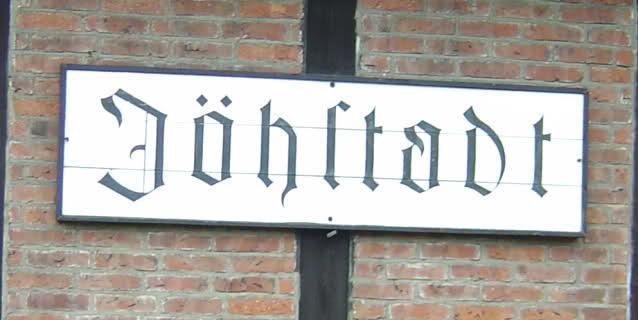
Frakturschrift gesucht
Welche Schrift wird auf diesem Bahnhofsschild verwendet?
Das ist handgemacht vom Schildermaler.
Was ja nicht ausschließt, daß sie auf einer bestehen Schrift basiert. Auch die Schriftenmaler haben sich das in den seltensten Fällen aus den Fingern gesaugt sondern Vorlagen benutzt.
Auch die Schriftenmaler haben sich das in den seltensten Fällen aus den Fingern gesaugt sondern Vorlagen benutzt.
Dann haben die aber oft eigene Schriftmusterbücher, die dann nicht unbedingt Druckschriften zeigen ...
Ja, es gab extra Vorlagenhefte für Schildermaler, z. B. vom Otto-Maier-Verlag in Ravensburg, die sind aber heute meist nicht mehr bekannten Druckschriften zuzuordnen, weil schon die Vorlagen geschriebene bzw. gemalte Alphabete waren.